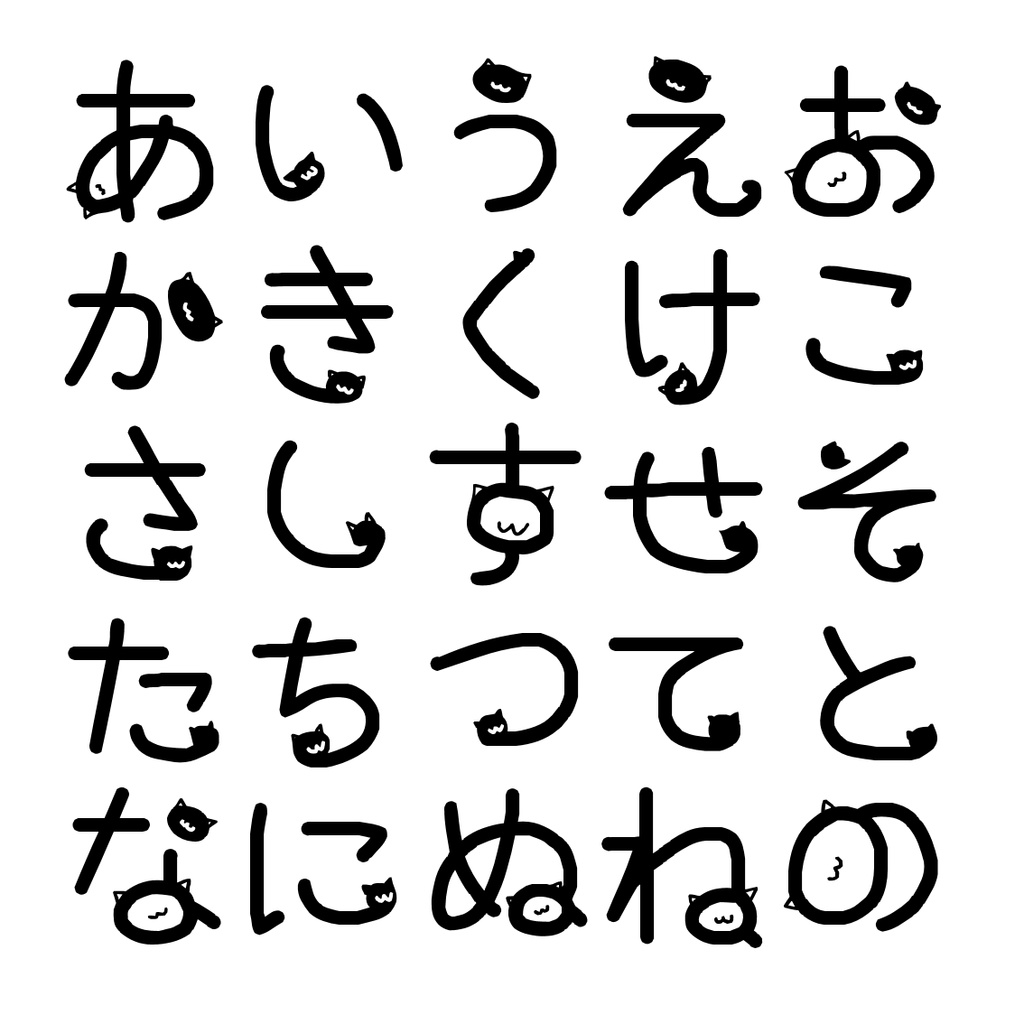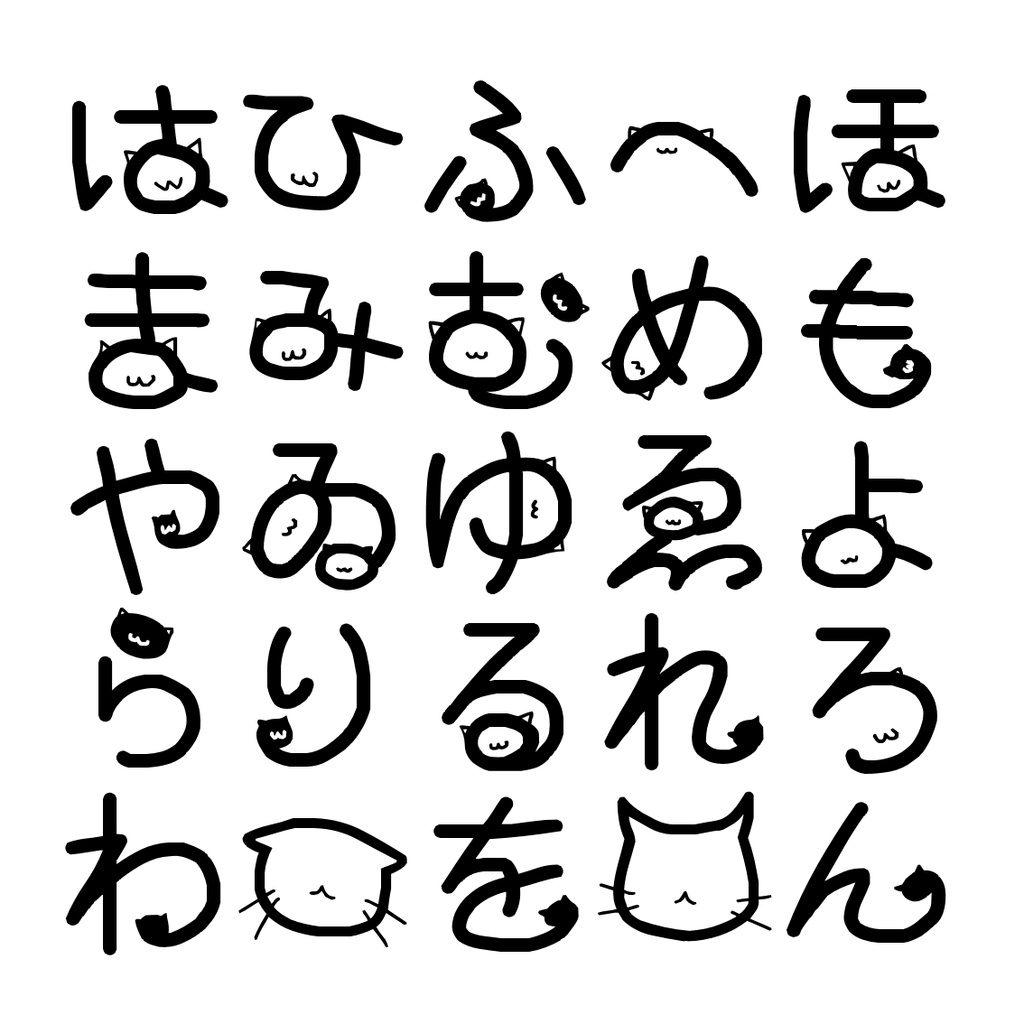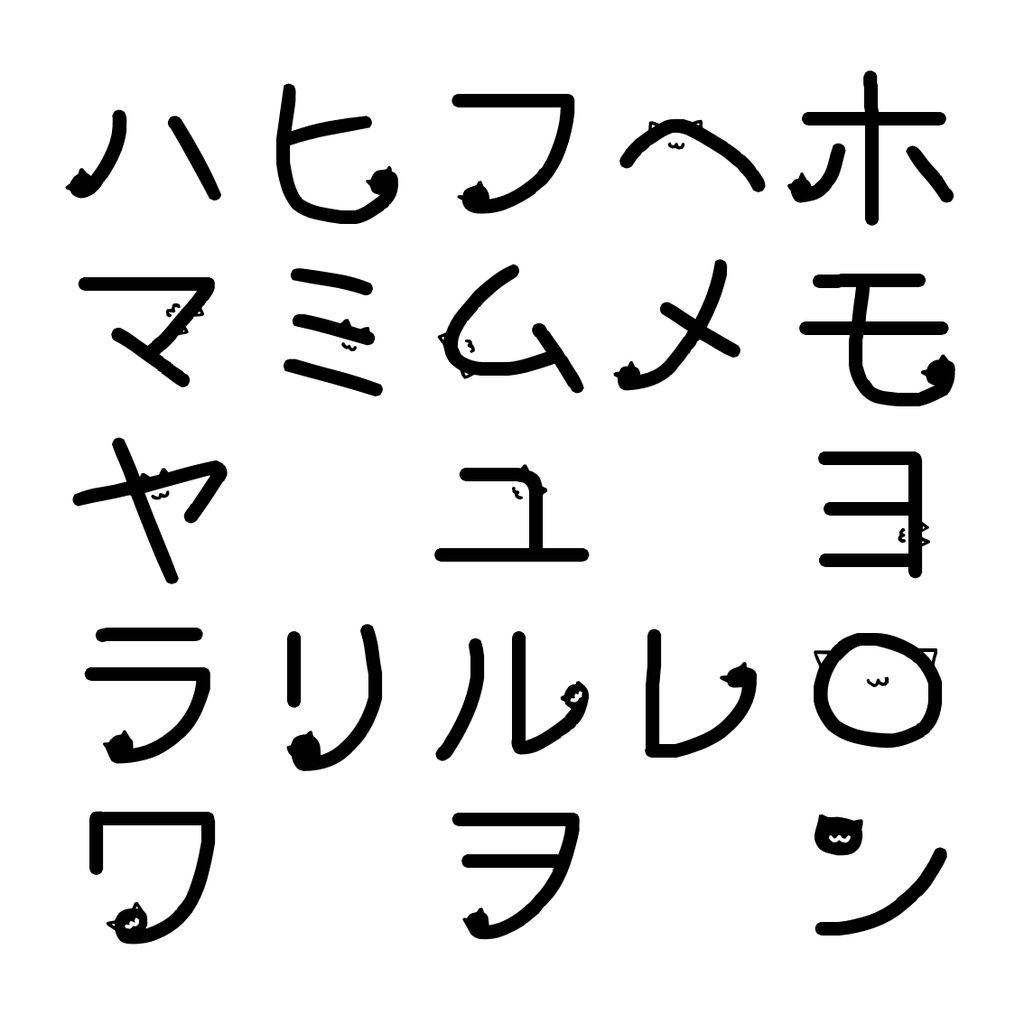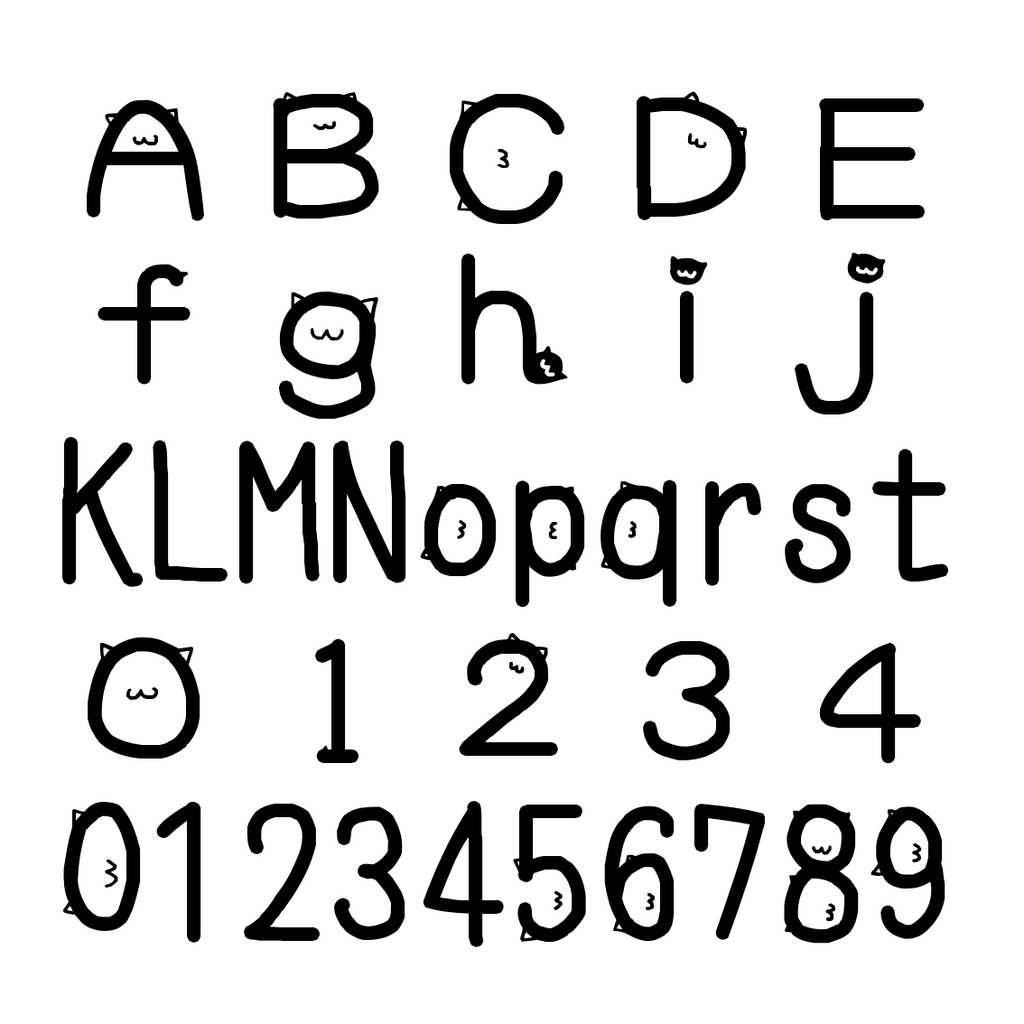
さりげ猫フォント【無料・商用利用可】
文字の中に、さりげなく猫が入っているフォントです。 平仮名・カタカナ・英数字の他、漢字は半端に少しだけ入っていますが、作成した本人である私がどこまで入れたか把握しておりませんので、入っている漢字はオマケ程度と考えてお使い下さいませ。 罫線の一部には絵文字が入っています。 全ての文字に猫が入っているわけではありません。 製作には武蔵システムのTTEditを使わせて頂いております。 漢字がほぼ入っていないのと、作成したのがかなり前のものなので無料にしております。 解凍後、出てきたTTFファイルをPCにインストールするとお使い頂けます。 ※フリーDLと支援版は同じものです。 【動作環境】 Windows:OS/日本語版WindowsXP〜11 フォント形式:TrueTypeフォント 【その他】 こちらのフォントを使用した作品等の商用利用は可能ですが、自作発言や再配布などはご遠慮下さい。